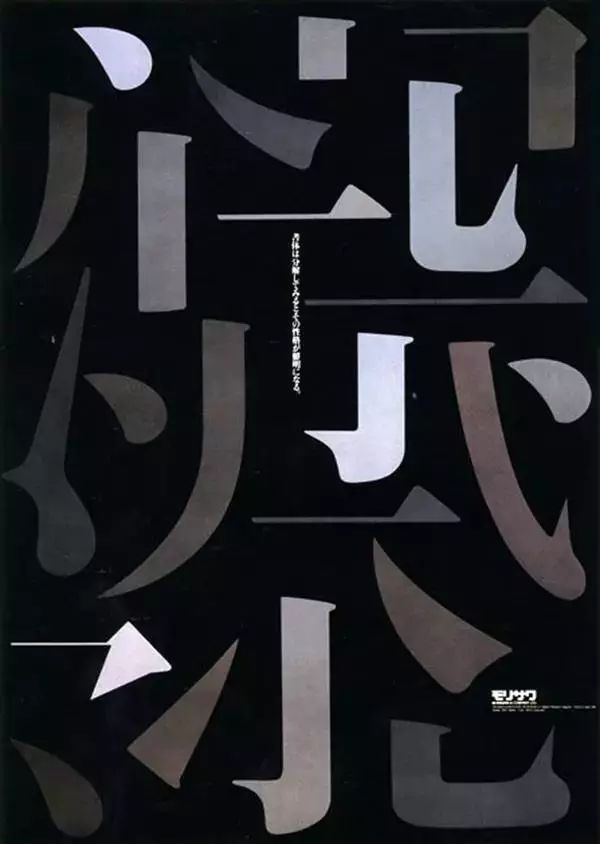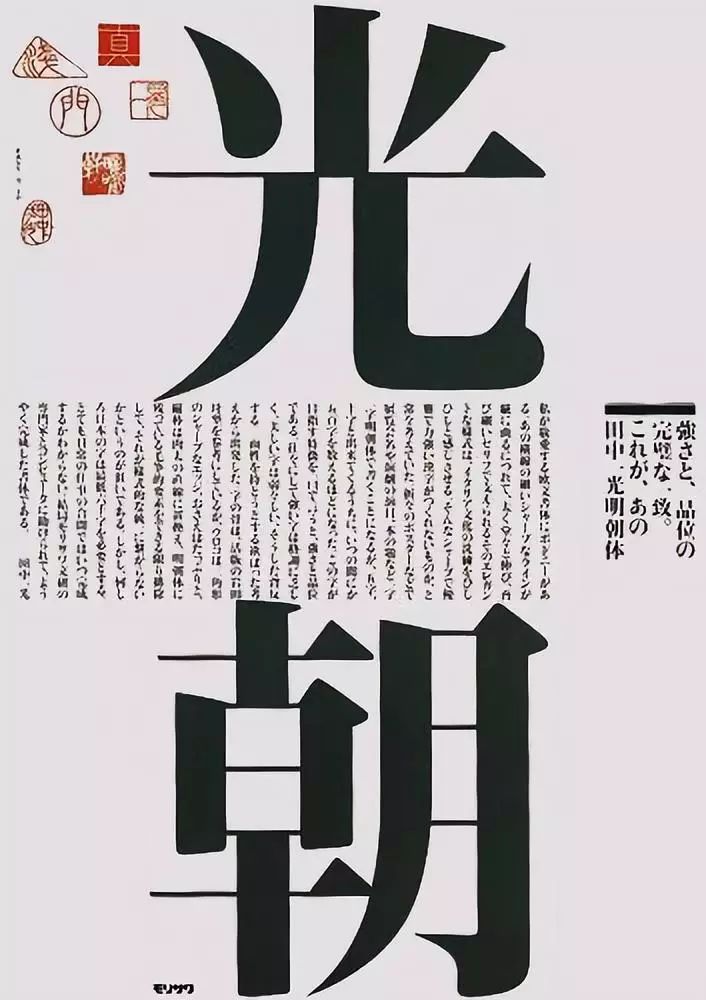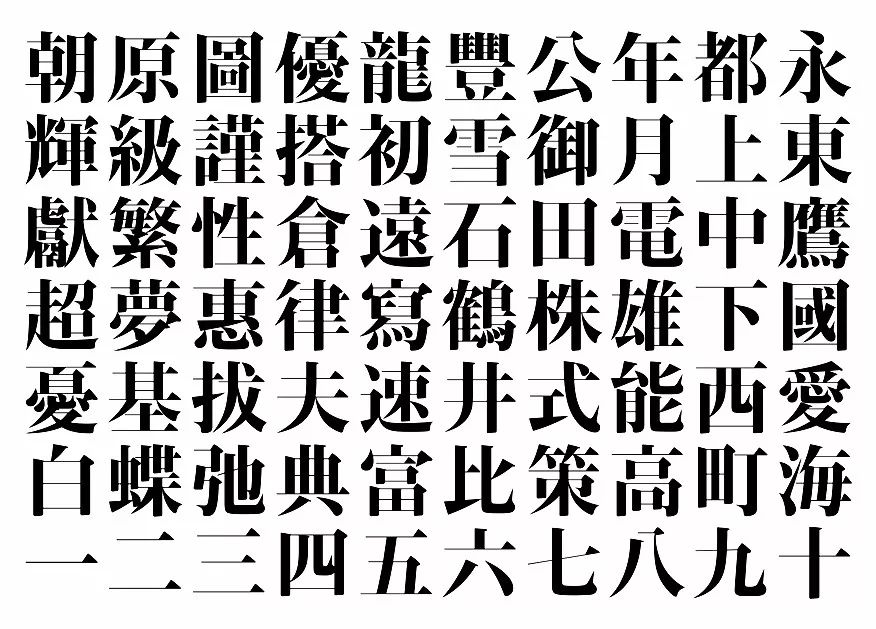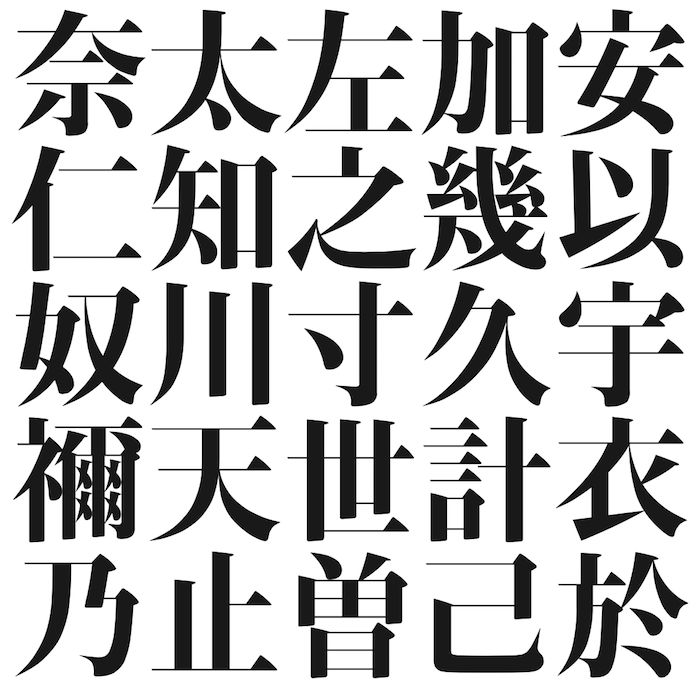
经典中的经典|田中一光の光朝書体
たなか いっこう
田中一光 Ikko Tanaka
1930—2002
日本最具代表性的平面設計師,设计界教父级人物。
1930年出生於古都奈良。1950年毕业于日本京都美术学院,后成立了日本设计中心。
同时也是无印良品的创始人之一。
他的设计理念对日本设计产生了及其深远的影响,甚至后来影响到整个世界。为今后日本在世界上的设计地位
作出了巨大贡献。
田中一光一生对传统文化,特别是日本的传统文化特别迷恋和追逐。
从日本的传统戏剧、哥舞伎表演,到日本的古建筑、神社、再到日本浮世绘、陶瓷、日本的文字,甚至是日本民间
的传统习俗,茶道,禅文化,无一不激发田中一光的设计灵感。
激发他对于日本设计发展的思考。田中一光的许多作品、绘画、平面设计、品牌设计,
都可以看到传统文化所带来的影响。一方面将日本传统文化融入到设计中去,让全世界了解日本传统文化,
接受日本设计;另一面他又将现代设计概念引入日本。
日本舞蹈 1981
这可能是田中一光最具代表性的海报,也是他将日本传统艺术转化为20世纪后期现代设计的完美案例。
这张海报已成为田中一光广为人知的标志了。
MUSIC TODAY 1985
田中一光喜欢运用图形和色彩,同时也敢于突破现代主义的界限。这张海报在外观、
感觉和趣味性上体现了现代主义化的后现代主义。
写乐二百年 1995
写乐是日本江户时代家喻户晓的浮世绘师,这是为写乐诞辰二百周年制作的命题海报。画面中用九个正圆形色块构成
几何化画面,眼睛和眉毛则是保留了写乐原作的笔画。
Kabuki歌舞伎 1974
田中一光擅长以民族文化为设计元素,创造出个人的强烈设计风格,把日本文化传统中的精髓继承下来,
而又大胆开拓出新表现方式,将平面分成若干的色块,通过变化色块的形状形成设计平面,并传达出历史的韵味。
他的成就,不仅仅是基于造型基础,
而且也是基于对历史遗产的深刻理解,对民族文化的深刻理解和到位的把握,还有对自己信念的坚持。
后人对他的评价:他开创了一个时代,是他一人的巨臂,让世界知道日本的现代设计。
こうちょう
光朝書体
田中一光的涉猎很广,对设计的各个领域都很有建树,他不仅自己是一代设计大师也为战后日本设计在世界站一席
之地做出了巨大贡献。 且对字体设计的贡献也很大,在字型开发上投注的心力,与在文字设计术(Typography)
上的贡献,深刻影响了汉字文化圈的设计。
以至后来创造出了经典的“一光明朝体”,特点是:横瘦、竖肥、角尖。
极具现代风格的文字之美
文字是平面设计的要素中,田中一光特别重视并探索不懈的项目。
1960至1970年代,贺伯.鲁巴林(Herb Lubalin)在纽约开启美国文字编排设计的盛世,
文字从此自辅佐的角色跃为设计的中心。
缪勒.布洛克曼(Josef Müller-Brockmann)在瑞士主张的「新图案」(die neue Graphic)
风靡流行,知性的文字编排从此确立了独立的地位。
青年时代的田中一光受到这股风潮影响,为日本设计界注入新思想。
他从手写开始,钻研活版字型与照像排版的组合,思索独特品格的文字,并创造「光朝」字体。
文字的想象力 1993
海报中通过对汉字笔划的拆解,用一种不拘一格、芭蕾舞似的形式展示了光朝字型的魅力。
1950年代起,印刷从铅字活版转型为照相排版,70年代大量新字体诞生,田中一光曾以「明石」、「龙明」
等为主题製作海报。
他为研究古代文字曾远赴埃及、希腊、土耳其等国家考察,并在中国再度认识到汉字的魅力。
受到优雅的义大利Bodoni字体启发,田中一光设计的明体字「光朝」端庄典雅,是他致力将文字做为设计主题的
一大成就。「光朝」以明体为基础,
参考岩田活版母型的初号(最大级数)活字,纵笔粗厚有力,横笔纤细轻盈,横线收笔部分的三角形光芒般锐利。
开始时他根据工作需求,一口气画了五百字以上,
后来在森泽(Morisawa)字型公司的协助下把字体扩充到了六千字的规模。
通过森澤(Morisawa)字型公司的协助下最终将其数字化制作完成的具有独创性的一款明朝体,
并于2004年开始发售。它极细的横画、锋利的三角形、粗壮有力的纵画构成了洗练、锐利、具有等同Didot、Bodoni
风格和明朝体元素的现代时尚造型。
高雅的气质与纤细的优美感,非常适合于海报、标题等大字号文字使用。